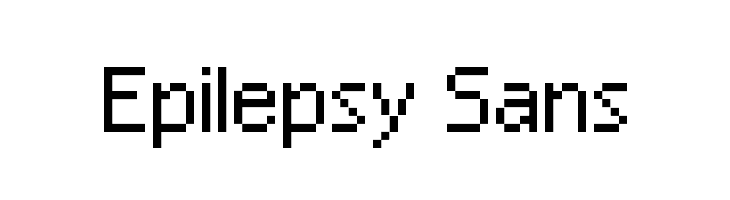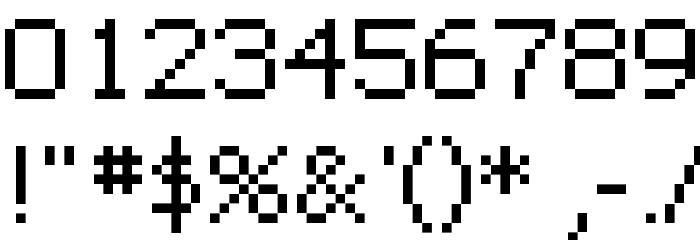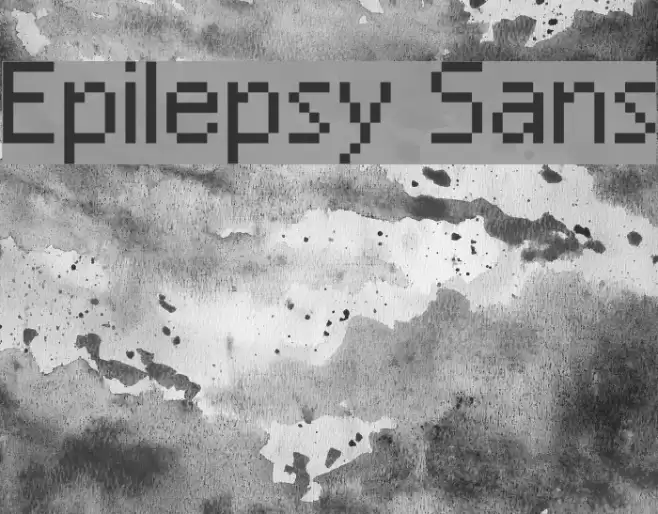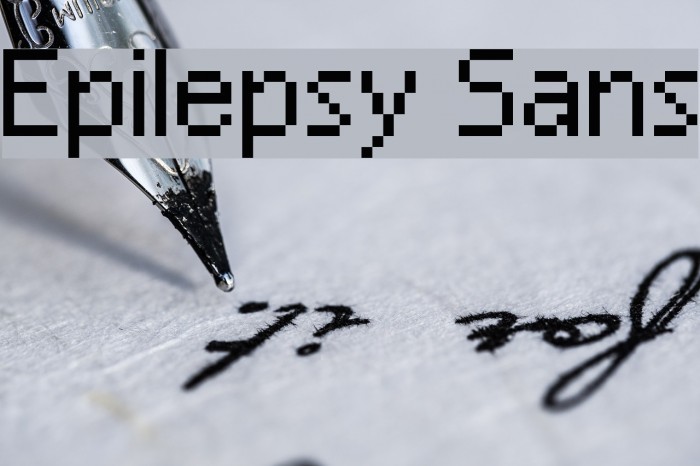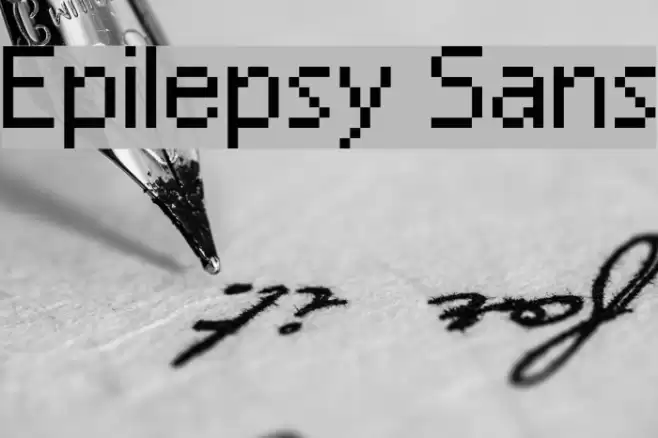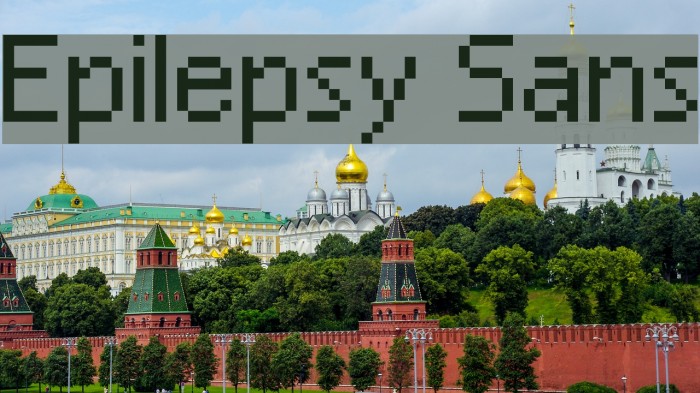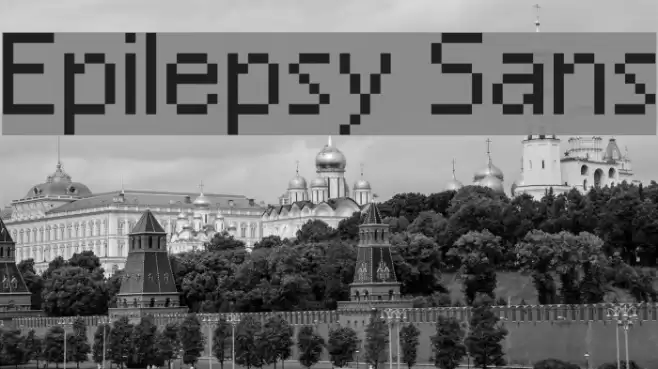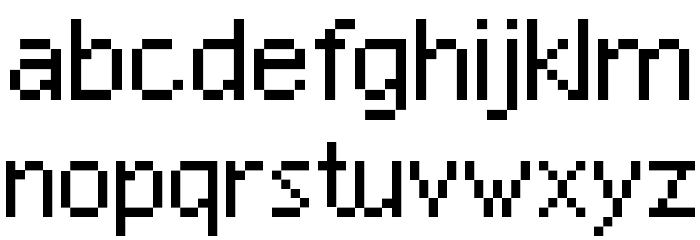
Epilepsy Sans Font
| Категория | Pixel |
| Общий стиль | Retro, Digital |
| Область применения | Logos, Digital displays, Video game graphics |
| Рекомендуемые проекты | Ideal for retro video game graphics, digital art projects, tech-themed posters, and any design requiring a vintage digital aesthetic. |